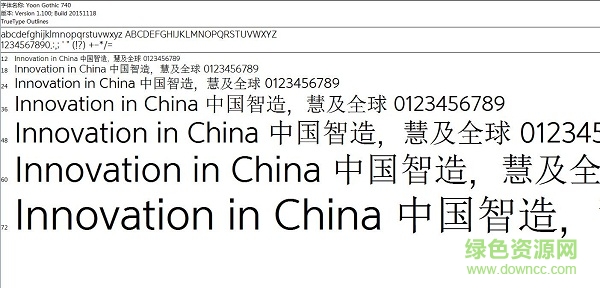
yoon gothic
yoon gothic字體是一款端正的韓文字體,這款無襯線字體撇捺舒展,表現(xiàn)力強,用在期刊、廣告、海報、宣傳設(shè)計等領(lǐng)域橫排豎列俱佳,喜歡的朋友快來綠色資源網(wǎng)下載吧!
字體氣質(zhì)介紹
【男性氣質(zhì)】
作為強現(xiàn)代感的無襯線字體—黑體,給人感覺粗壯緊湊,頗有力量感,可塑性很強,即可表現(xiàn)為陽剛有力的男性氣質(zhì),也可以變成纖細(xì)優(yōu)雅的女性氣質(zhì)。
yoongothic
【女性氣質(zhì)】
字如其人,女性的特點是細(xì)致優(yōu)雅、苗條細(xì)長;常被用作化妝品、女性雜志、藝術(shù)等女性主題領(lǐng)域。
【文藝氣質(zhì)】
宋體的衍生有很多,又長有扁,有胖有瘦。一般用于書籍印刷。而在電影界上這類型字體多用于文藝片